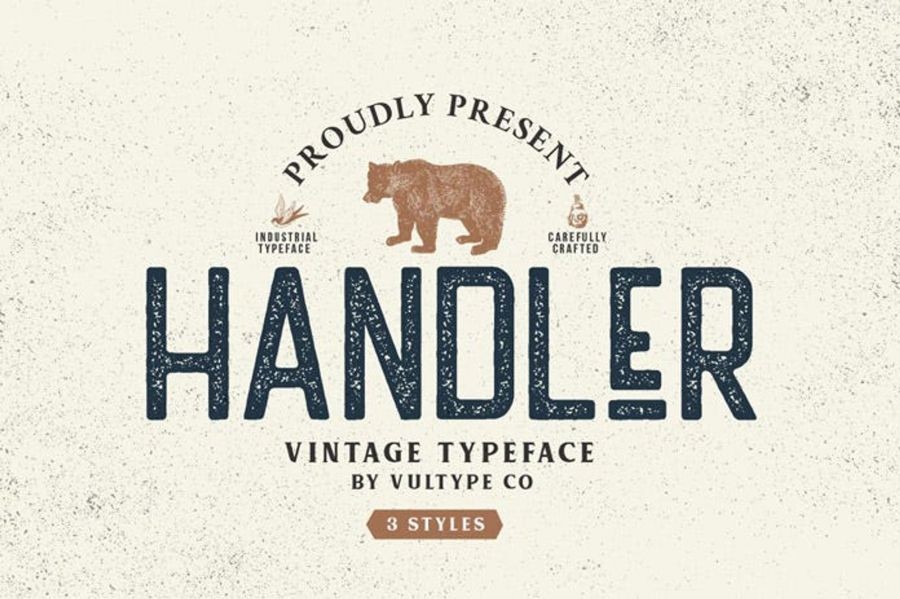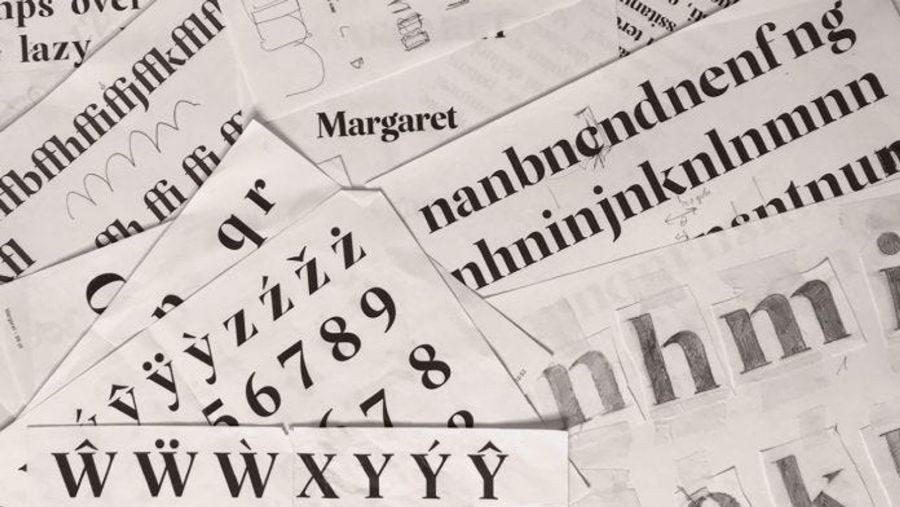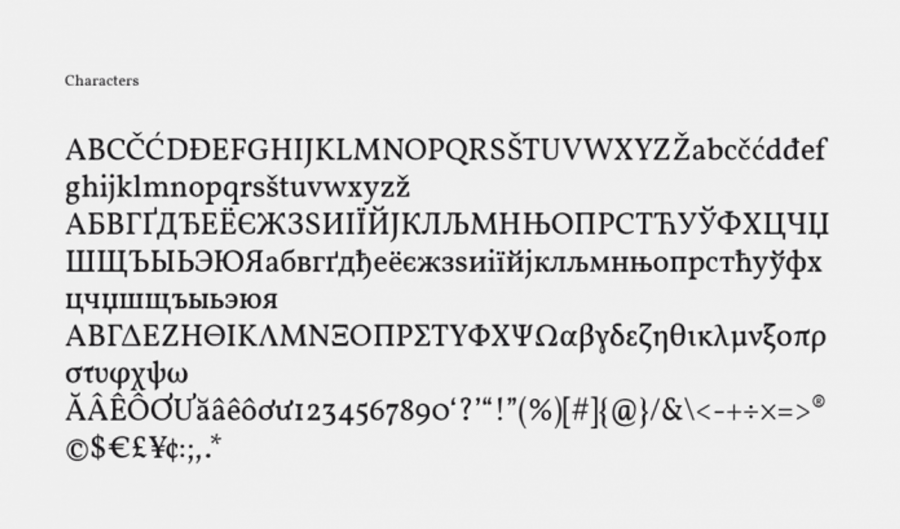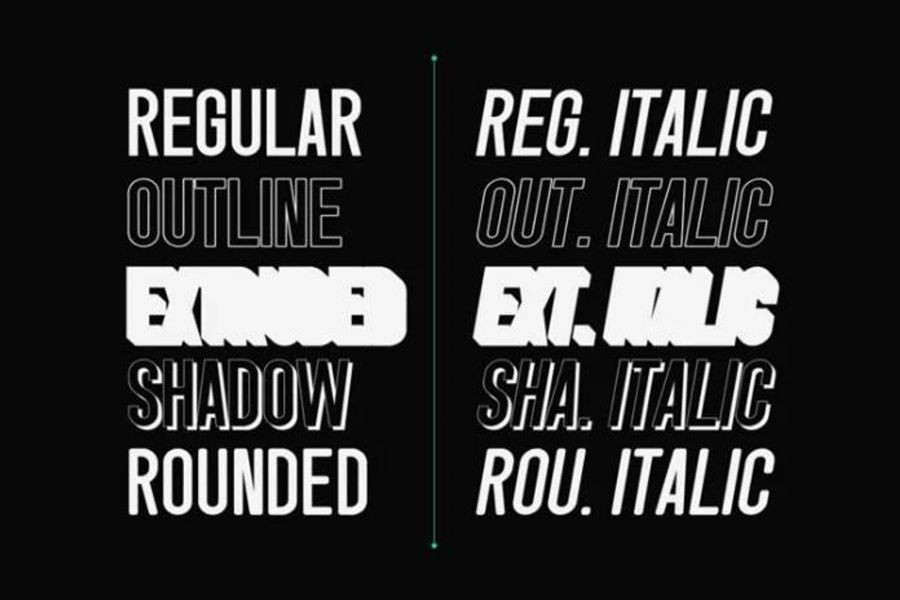
2024년,
디자이너를 위한 최고의
무료 폰트 5개
디자인에 세련미, 대담함, 빈티지 감성을 더해줄
필수 타이포그래피
타이포그래피는 메시지를 전달하고 프로젝트의 시각적 매력을 풍부하게 만드는 중추적인 요소로서 그래픽 디자인에서 엄청난 중요성을 갖습니다. 다행스럽게도 디자이너는 자신의 디자인을 더욱 돋보이게 하는 다양한 무료 글꼴을 활용할 수 있습니다. 수 많은 무료 글꼴을 철저히 조사한 후 2024년에 다운로드할 수 있는 그래픽 디자이너를 위한 최고의 글꼴 컬렉션을 선별했습니다. 앞서 언급했듯이 우리가 선택한 글꼴은 무료로 사용할 수 있으며 개인용 및 상업용 모두에 대한 옵션을 제공합니다.
5. Handler - 빈티지 산세리프 글꼴
향수를 불러일으키는 빈티지 폰트 Handler! 레트로 스타일에서 영감을 받은 이 글꼴은 일반, 스탬프, 러프 변형으로 구성된 다양한 문자 배열을 제공합니다. 원활하게 혼합하거나 독립적으로 사용하여 프로젝트나 디자인을 사로잡는 독특한 요소를 만들 수 있습니다. 로고, 브랜딩, 빈티지 의류, 패키지 등에 이상적입니다. Handler는 다재다능함을 보여주며 다양한 창의적인 응용 프로그램에 매우 적합합니다!
4. Margaret - 세리프 글꼴
Kacper Janusiak과 K94 Studio의 재능 있는 팀이 제작한 매우 우아한 Margaret Serif 글꼴은 시대를 초월한 매력과 세련미를 발산합니다. 무료로 제공되는 헤드라인, 브랜딩 노력, 로고타입에 맞춰 제작된 이 세리프 글꼴은 창의적인 프로젝트에 세련된 매력을 원활하게 불어넣습니다.
3. Vollkorn - 무료 Google 글꼴
Vollkorn은 디자인 원칙에서 영감을 받은 세리프 글꼴 계보를 나타냅니다. 이 글꼴은 단 2년 만에 수천 건의 다운로드를 기록하면서 빠르게 인기를 얻었습니다. 현재 Vollkorn은 네 가지 고유한 두께(일반, 세미 볼드, 볼드 및 검정색)를 제공하는 Google 글꼴로 쉽게 사용할 수 있으며 각 글꼴에는 해당 이탤릭체가 표시됩니다. 눈에 띄고 실질적인 세리프로 주목할만한 Vollkorn은 인쇄 및 웹 디자인 추구를 쉽게 수용합니다.
2. Singo
대담함을 자랑하는 시선을 사로잡는 디스플레이 글꼴인 Singo는 날카로운 모서리와 우아한 곡선으로 시선을 사로잡습니다. 영향력 있는 문구에 맞춰 제작된 이 산세리프 글꼴 모음은 다양한 창의적인 길을 열어줍니다. 5가지 글꼴 스타일, 10가지 글꼴 모음, 2,000개 이상의 광범위한 글리프 배열을 자랑하는 Singo는 디자이너를 위한 다용도 역할을 합니다. 인도네시아에 뿌리를 둔 Singo의 본질은 디자인에 강인함, 대담함, 용기를 반영합니다.
1. Big John Pro
Big John PRO는 오랫동안 사랑받는 무료 글꼴 컬렉션 중에서 특별한 위치를 차지하고 있습니다. Ion Lucin이 제작한 이 글꼴은 Big John 및 Slim Joe 글꼴의 개선된 버전으로, 이 링크를 통해 편리하게 액세스할 수 있습니다. 이 Pro 버전은 굵은 글꼴, 밝은 글꼴 및 일반 글꼴 스타일을 포함하여 개인용 및 상업용 모두에 원활하게 적용됩니다. 이 모든 것이 무료입니다!
2024년 상위 5개 무료 글꼴 라인업이 향후 프로젝트에 이상적인 폰트를 찾는 데 도움이 되기를 바랍니다.